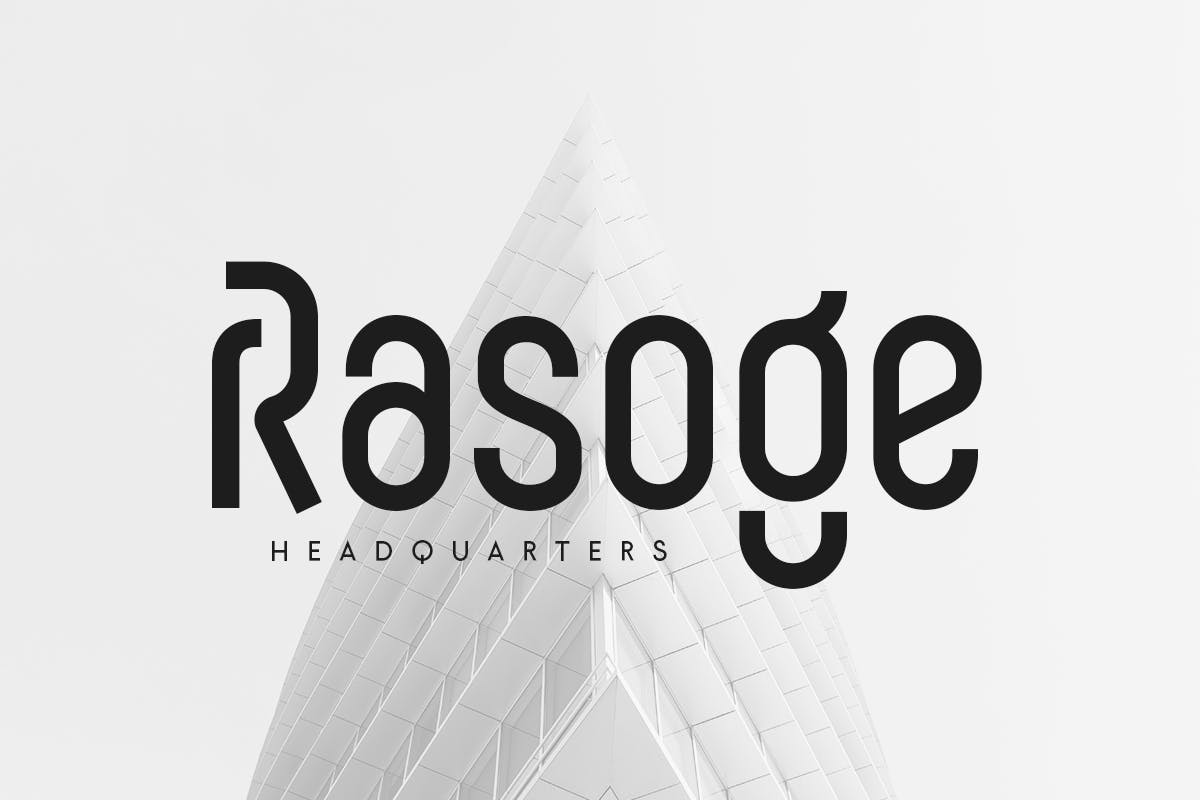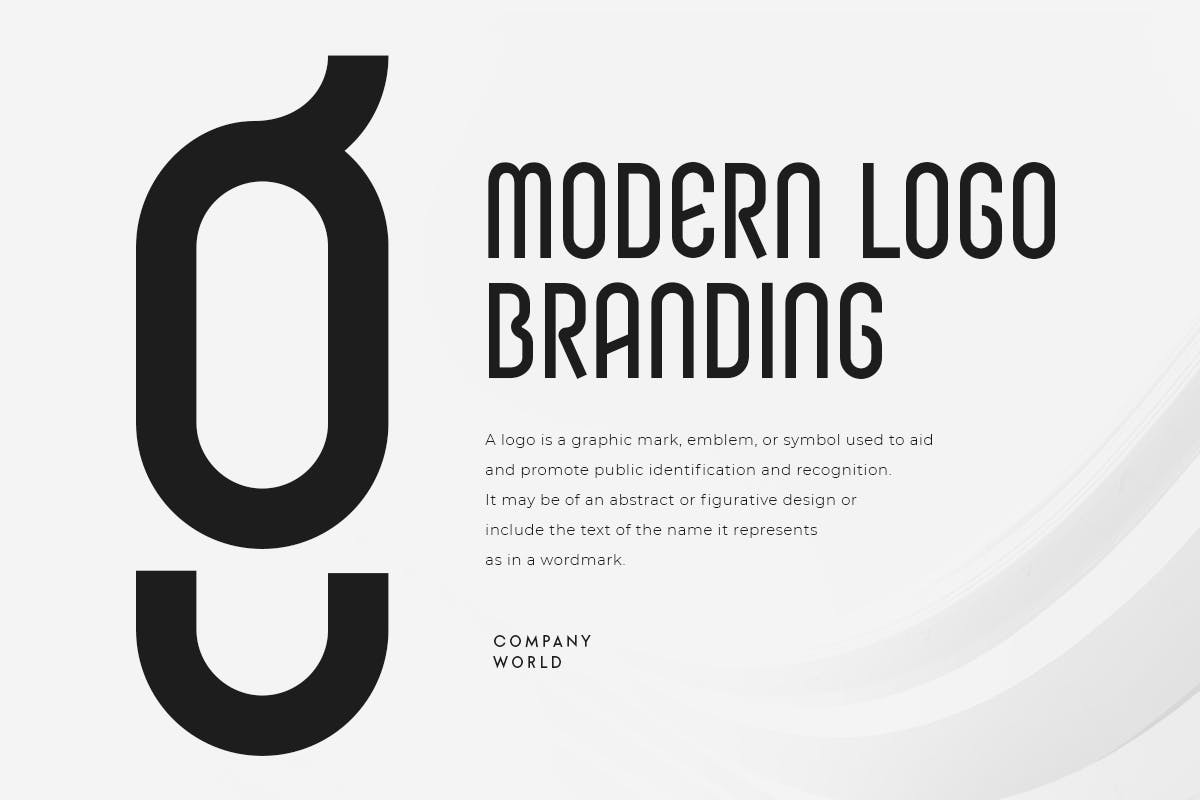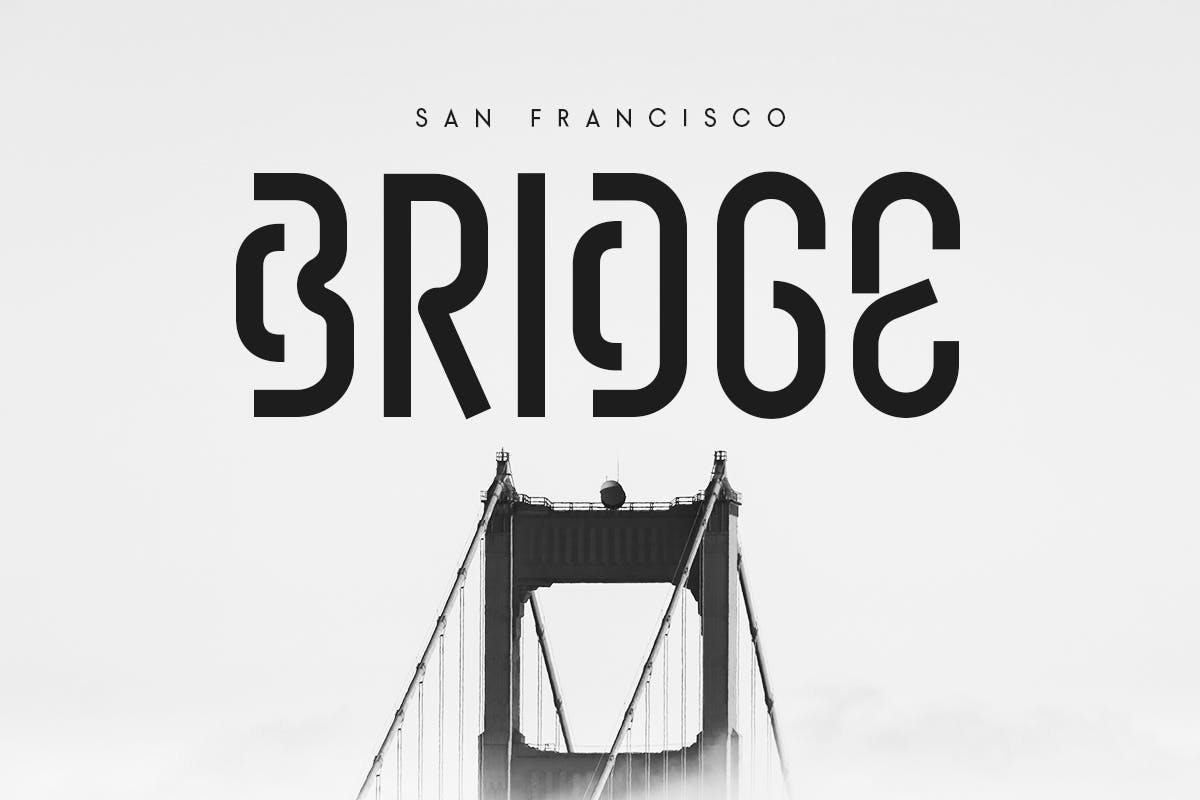
فونت لوگوتایپ مدرن یک فونت منحصر به فرد است که بهطور ویژه برای نیازهای برندینگ حرفهای و مدرن طراحی شده است، که به شما ظاهری منحصربهفرد میدهد. این فونت با اشکال خاص و متنوع خود، آماده است تا ارزش برند شما را افزایش دهد. این فونت برای طراحان و صاحبان محصولات که به دنبال راهحلهایی برای حرفهایتر و مدرنتر کردن طراحیهای خود هستند، بسیار مناسب است. بهویژه برای این فونت، ما کاراکترهای متنوعی را آماده کردهایم تا به شما در ایجاد واریاسیونهای نامحدود برای نیازهای خلاقانهتان کمک کنیم.